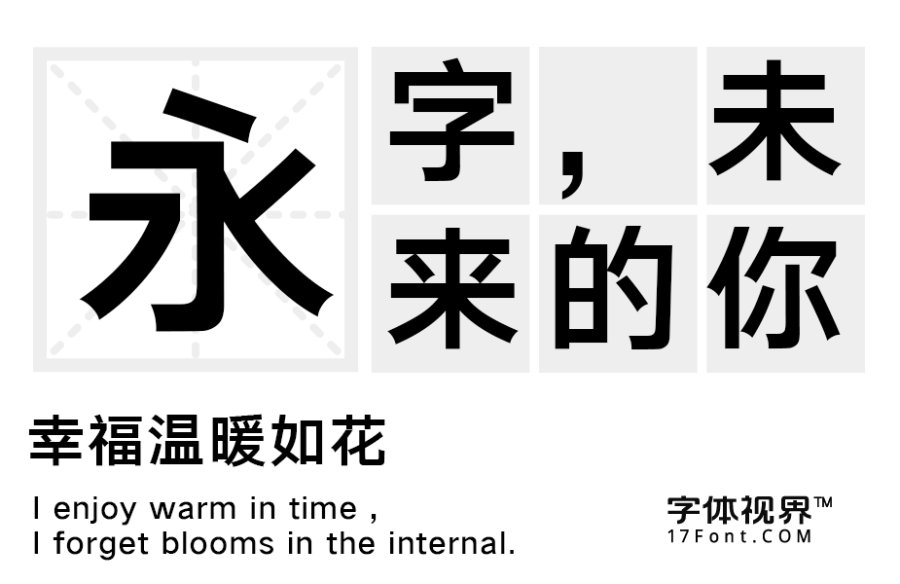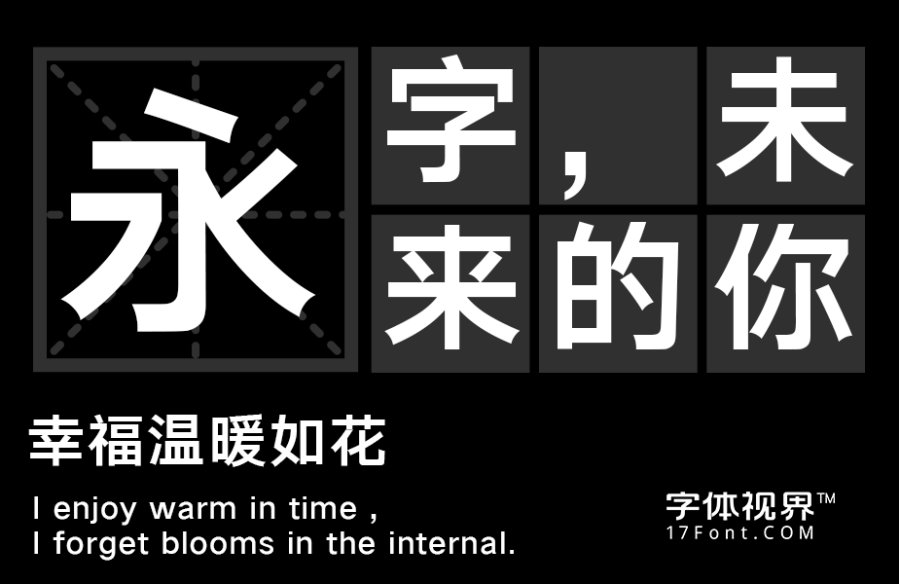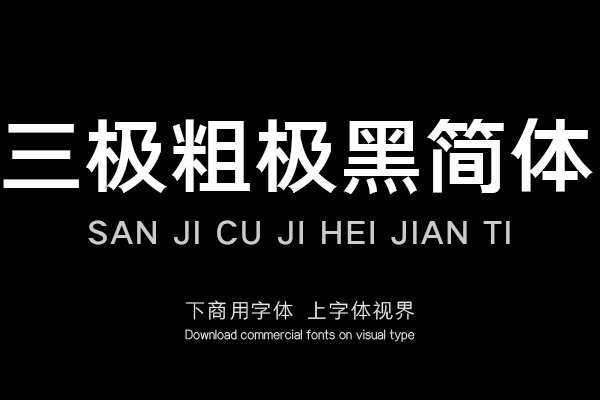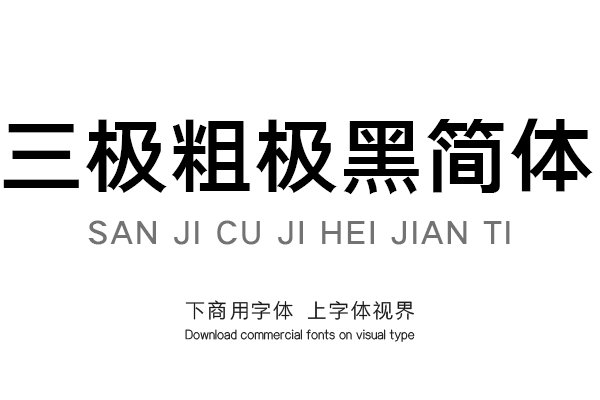
三极粗极黑简体是一款家族字体,字形清新,结构严谨,布白均匀,中宫偏大,重心一致。适当缩小字面大小、加大默认字距、增强了字体的识别性,使得版面更加通透明了。字形更......购买须知:“下载服务费”与“字体VIP”所获得字体 仅用于个人非商用, 商用请联系付费授权。本字体为电脑用字,手机没有root权限不支持直接手机换字(手机如何root,请自行百度搜索教程)。购买前请先 了解清楚后再付款 ,字体为虚拟产品无法回收 一旦购买不支持退款。